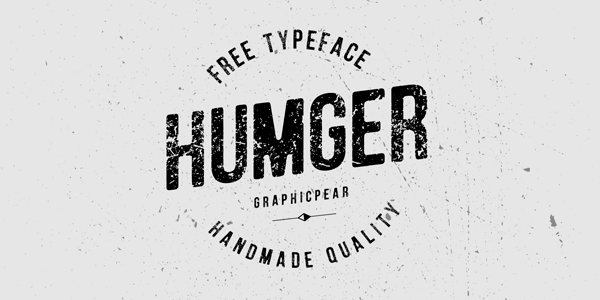
【トレンドは大胆×キャッチー】2017年の注目フォント10選!!
2017年も数カ月が過ぎましたが、この間にもWebデザイン業界ではたくさんのトレンドが生じてきました。
全般的にいって、2017年はコンテンツを強調するレイアウトの一年になると言えるでしょうが、加えて、Webサイトの個性を出すために、大きくて大胆なフォントタイプが流行したり、背景色として眩しいぐらいに明るい色遣いがなされたり、といったことが見られます。
この文脈で言っても、タイポグラフィ―はユーザの注目を集めるためにとても重要な要素となっています。
この記事では、2017年のメインストリームを形成すると考えられるフォントを、10紹介します。
AKROBAT
Akrobat
モダンな雰囲気を醸し出すフリーフォントです。文字と文字の間がぎゅっと詰まっているところが特徴で、見出しやロゴ、キャッチコピーなどに適しています。ラテン語などを含む様々な言語に対応しています。
HUMGER
humger
大文字オンリーのグランジスタイルのフリーフォントです。ストリートなどのすさんだ印象を連想させるオールドファッション。ロゴなどのアイキャッチに長けているので、アクセントをつけたいときなどに使用します。
SOPHIA
sophia
甘くて、生意気で、少し崩れた形状がコンセプトのフォントで女性がデザインしました。インフォグラフィックやロゴなど活用することが出来そうです。このフォントは、筆記体になるようになっているので、文字間隔はありません。
TUNA
tuna
このTUNAというフォントは、雑誌やモバイルアプリケーション、本などに活用されることを想定してデザインされました。そのため読みやすい書体になっています。5つの設定が存在しており、Light、Regular、Medium、Bold、Heavyからテイストを選ぶことが出来ます。
TOWN
town
今風な印象を強く与えるフォントです。設定も自在にでき、8つのウェイト、9つのスタイルから設定することができますが、購入するパッケージによって変わってきます。
MADELYIN
madelyn
このMADELYINというフォントはハンドライティングを模したフォントです。大文字小文字、パンクチュエーション、数字などの細部までこだわってデザインされています。ブランディンを意識したサイトなどにはもってこいです。
KLASIN
klasik
このファミリーフォントはシンプルで機能的なコンセプトでデザインされています。レギュラー、ラフ、シャドウと3つの違ったスタイルが用意されています。インフォグラフィック、ポスター、見出しなどの高いデザイン性を必要とするものに適しています。
PROXIMA SOFT
proxima-soft
このPROXIMA SOFTというフォントは既に存在するPROXIMA NOVAに丸みを足した改良版のデザインです。48の違ったデザインと8つの濃度、斜体のオプションなども含まれています。
ANDIS
Andis
正にデジタル世界の文字という印象を与えるフォント。太さやスタイルなどを変えることによって、見出しやロゴにも活用できます。シンプルな分読みやすいのも特徴的です。
KAPPA
kappa
このフォントは人間的でもあり幾何学的でもあるモダンな印象を与えます。文字の構成は、平均よりも文字間隔が狭めで、高さもある程度あるので読みやすさも問題ありません。このフォントは9つの濃度とイタリックのオプション、2つの違ったバージョンを提供しています。